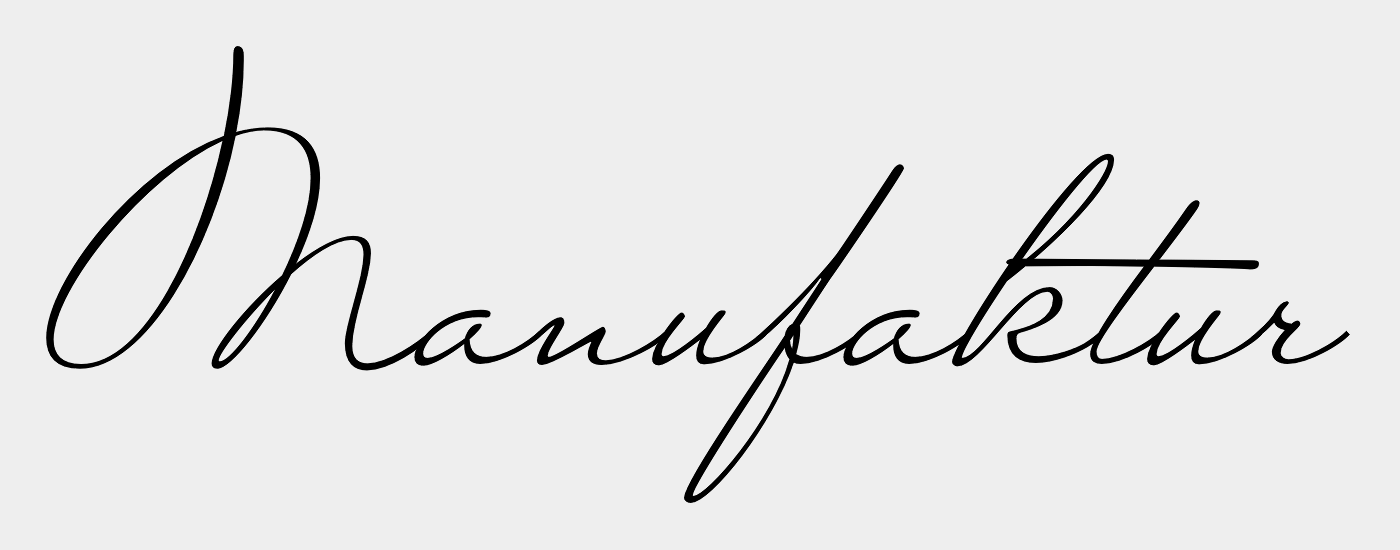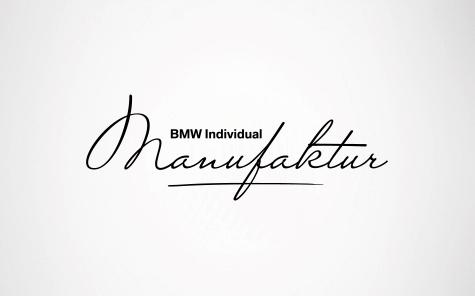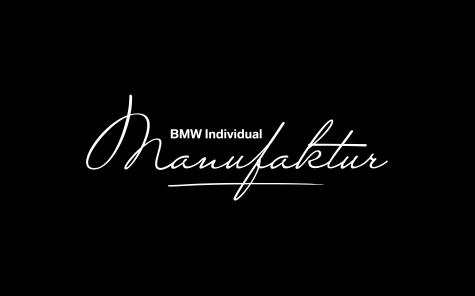
Suche Schriftart von BMW Individual Manufaktur
ich suche diese elegante Schriftart (Handschrift) von BMW Individual Manufaktur.
Wär ja direkt peinlich, wenn eine "Individual Manufaktur" eine Schrift von der Stange verwendet … :-|